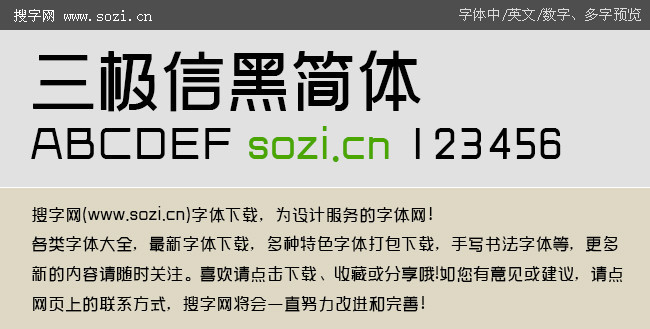
三極信黑簡(jiǎn)體
搜字網(wǎng)給大家提供一款三極信黑簡(jiǎn)體字體下載,三極信黑簡(jiǎn)體是三極字庫(kù)所推出的一款以黑體字形為基礎(chǔ)的設(shè)計(jì)字體。該字體筆鋒有力,筆畫設(shè)計(jì)端正大方,用于文章標(biāo)題會(huì)有非常醒目的視覺(jué)效果,適合應(yīng)用于書籍設(shè)計(jì)、平面海報(bào)設(shè)計(jì)、包裝設(shè)計(jì)等廣告應(yīng)用。(本字體為個(gè)人非商用版,如需要商用請(qǐng)聯(lián)系作者購(gòu)買版權(quán))